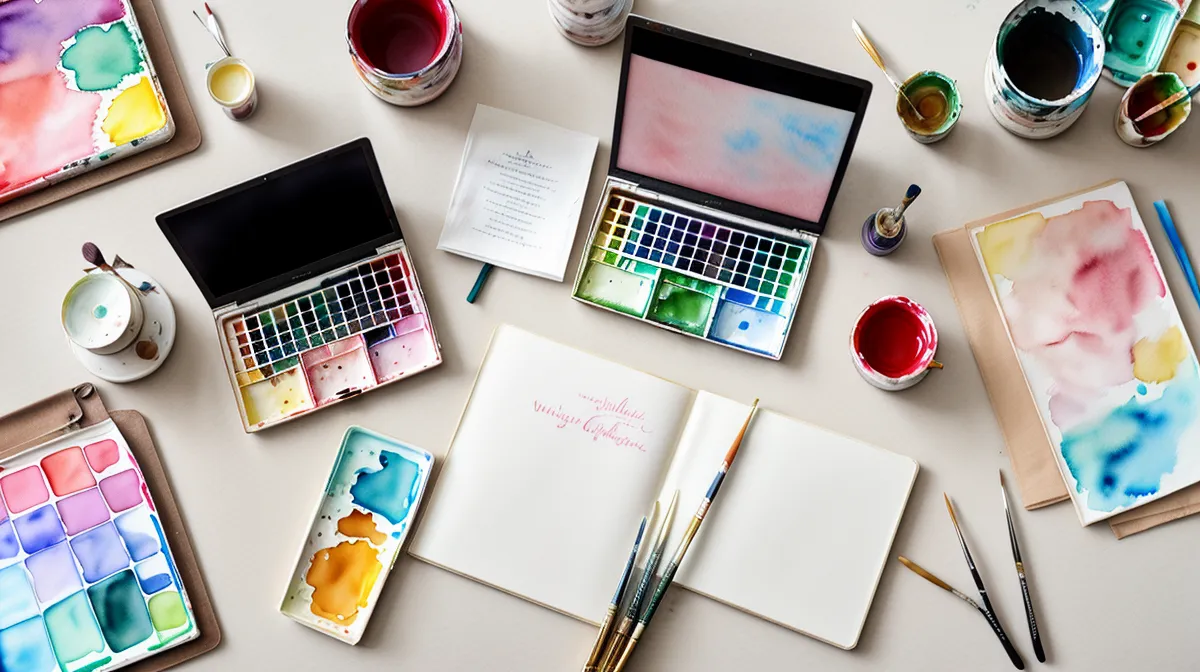
Aquarellpapier mit einem Flächengewicht von mindestens 300 Gramm pro Quadratmeter hält Wasser aus, ohne sich beim Trocknen zu wellen. Diese eine Zahl kläre ich zuerst, wenn mich jemand nach der Aquarell-Technik im Handlettering fragt, denn ohne das richtige Papier bringt kein Handlettering-Kurs und kein Tutorial saubere Farbverläufe zustande. Aquarell-Lettering ist als kreatives Hobby vor allem eins: eine Materialfrage, keine Talentfrage. Die Fragen, die mir dazu am häufigsten gestellt werden, beantworte ich hier der Reihe nach.
Welches Papier verträgt nasse Farbverläufe?
Standard-Papier für Brush Pens ist für Aquarell-Lettering ungeeignet, weil es zu glatt und zu dünn ist. Sobald Wasser ins Spiel kommt, braucht die Faser Stabilität, sonst verzieht sich der Bogen wie dünne Wellpappe. Aquarell-Lettering hat eine eigene Papier-Stift-Logik, die sich fundamental von klassischem Brush Lettering unterscheidet. Ein Papier, das für Fineliner perfekt ist, versagt beim ersten nassen Strich.
Kaltgepresstes Papier (cold pressed) hat eine Struktur, die Wasser anders hält als das glatte, heißgepresste Papier. Für Lettering ist das ein Dilemma: Struktur hilft dem Aquarell-Effekt, aber Glätte hilft den Pinselhaaren. Ich bin bei einem Papier mit 100 Prozent Baumwollanteil hängengeblieben, weil die Pigmente dort kontrolliert einsinken statt nur auf der Oberfläche zu schwimmen.
Farbe auf der Pinselspitze statt auf der Palette
Viele Einsteiger-Guides empfehlen, Wunschfarben auf einer separaten Palette zu mischen. In meiner Praxis führte das eher zu blassen, ausgewaschenen Ergebnissen als zu kräftigen Verläufen. Die Alternative, die gegen die klassische Lehrmeinung verstößt: Farbe direkt auf die Pinselspitze auftragen statt vorher zu mischen.
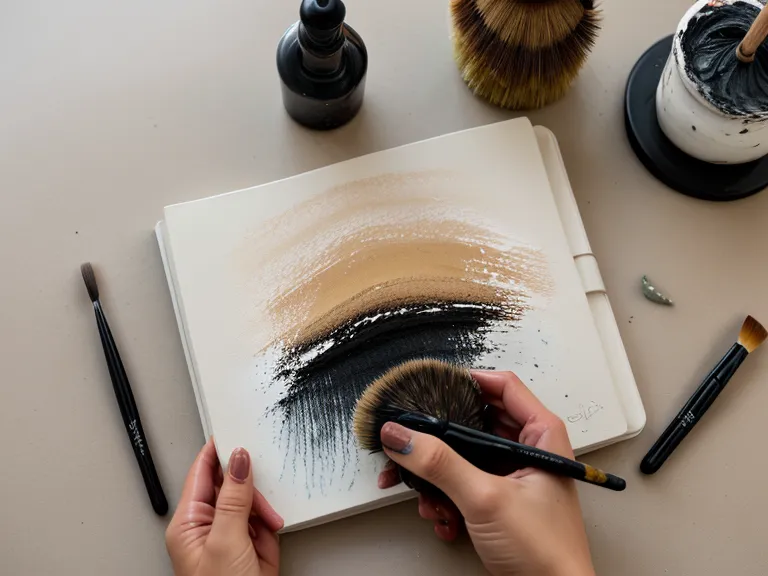
Mit einem Pinsel der Größe 2 nehme ich eine helle Farbe auf und tunke nur die äußerste Spitze kurz in ein dunkleres Pigment. Beim Ansetzen des Buchstabens beginnt der Strich dunkel und geht von selbst in die hellere Nuance über, ganz ohne manuelles Verblenden. Wie viel Druck dabei auf den Aufstrich kommt, ist reine Druckkurve, ein Thema, das für sich genommen einen ganzen Artikel füllt und hier nur die Grundlage für den Farbwechsel liefert. Ober- und Unterlängen sauber zu treffen ist wiederum eine Frage der Buchstaben-Anatomie, die ich an dieser Stelle nicht aufrolle.
Meine Finger sehen an solchen Abenden aus, als hätte ich ohne Handschuhe in Tinte gebadet, und auf der Tischdecke sammeln sich Flecken, die keine Wäsche mehr herausbekommt. Diese Momente gehören dazu: Der kurze Atemstillstand, wenn der Wassertropfen die Farbkante berührt und sich die Pigmente von selbst vermischen, entscheidet darüber, ob der Buchstabe Tiefe bekommt oder ob wieder nur der Lappen hilft.
Wie viel Übung braucht ein sauberer Verlauf?
Wie viele Übungsseiten das im Schnitt braucht und wie sich Fortschritt über die Zeit misst, behandle ich ausführlicher im Artikel zum Übungsvolumen beim Handlettering. In den gut drei Jahren, in denen ich mich systematisch durchs Lettering arbeite, hat sich vor allem eins bestätigt: Geduld schlägt Talent, und zwar deutlich.
Neulich habe ich ein frisches Übungsheft aufgeschlagen, und noch bevor der Pinsel das Papier berührte, wusste ich, auf welcher Seite ich anfangen wollte: bei den hellen Verläufen, nicht bei den dunklen Druckstellen. Das war keine plötzliche Erleuchtung, nur die Handschrift des Wassers, die sich irgendwann von selbst einprägt.
Pinsel und Pigmente, die den Unterschied machen
Vor einer Weile habe ich meine alten Billigfarben aussortiert. Ihnen fehlte die Pigmentdichte, um auf schwerem 300-Gramm-Papier zu bestehen. Was ich lange für mangelndes Talent hielt, war die minderwertige Bindung der Farbe: Echte Aquarellfarbe besteht aus Pigment und einem Bindemittel wie Gummi Arabicum, und bei günstigen Sets ist der Füllstoffanteil oft so hoch, dass die Farbe nach dem Trocknen stumpf und kalkig wirkt.
Am Anfang habe ich mir in einem Buchladen ein Kalligraphie-Set gekauft, randvoll mit Federn und Tusche für Spitzfeder-Schrift. Für Brush Lettering war davon nichts zu gebrauchen, und das Set liegt bis heute unangetastet in einer Schublade. Es hat mich gelehrt, vor dem Kauf genauer zu lesen, wofür ein Set eigentlich gedacht ist.
Ein Pinsel der Größe 2 ist für die meisten Lettering-Details ideal: groß genug, um einen ganzen Buchstaben ohne Absetzen zu schreiben, fein genug für hauchdünne Aufstriche. Synthetikhaare sind für Anfänger oft leichter zu kontrollieren, weil sie mehr Spannkraft haben als Echthaar-Pinsel, die manchmal fast zu weich reagieren. Der erste Handgriff bei einem neuen Brush Pen ist immer derselbe: Deckel ab, ein kurzes, tiefes Klack-Geräusch, und man merkt sofort, ob die Spitze frisch ist oder in der Schublade schon halb ausgetrocknet lag. Wie schnell so ein Pen sich dabei abnutzt und woran man das erkennt, ist noch mal ein eigenes Thema, das ich im Vergleich der besten Brush Pens für Einsteiger auflöse.
Aquarell-Lettering bleibt ungefähr so, wie ich es aus dem Kurs mitgenommen habe: zu 30 Prozent Technik und zu 70 Prozent Geduld mit dem Material. Wer dem Papier Zeit zum Trocknen gibt, bevor die nächste Schicht kommt, bekommt saubere Verläufe. Wer das überspringt, landet wieder bei einem matschigen Fleck statt bei einem Farbverlauf, der wie eine Welle aussieht.